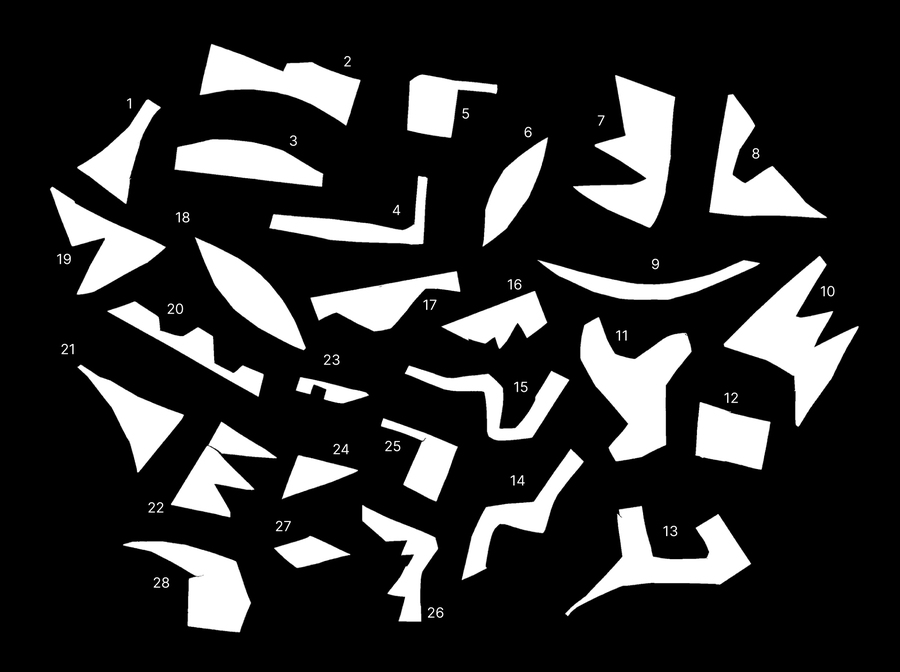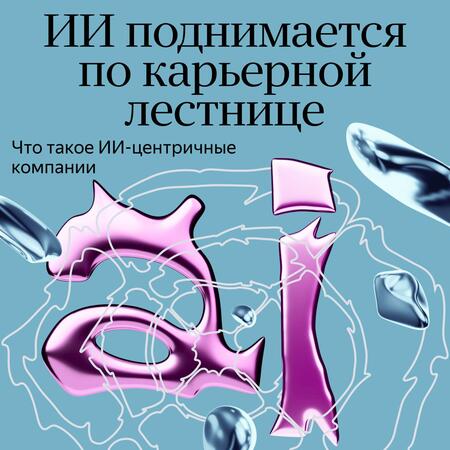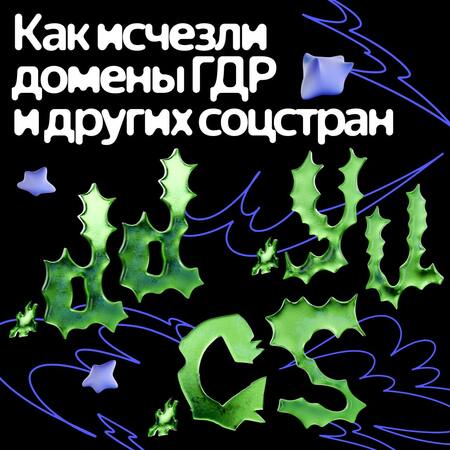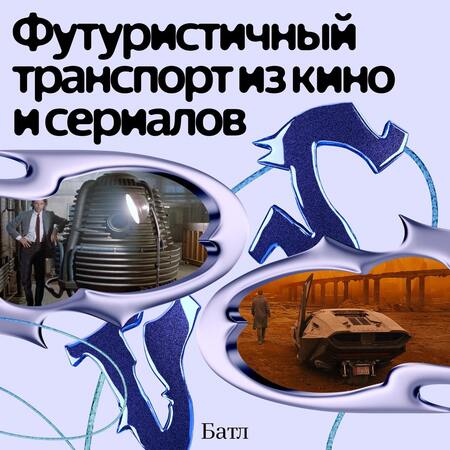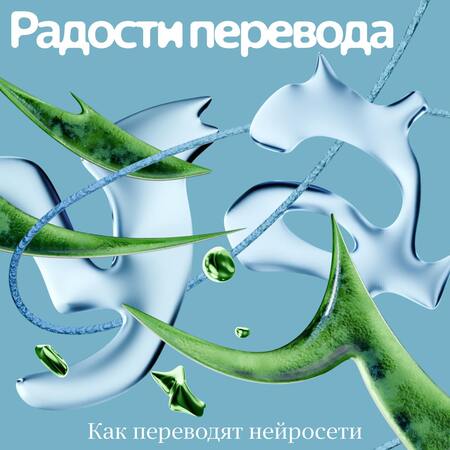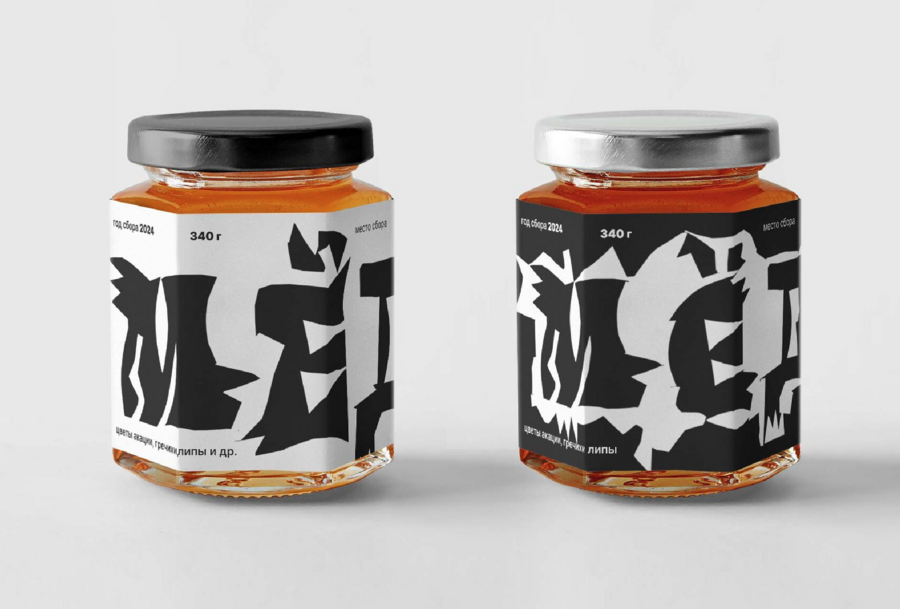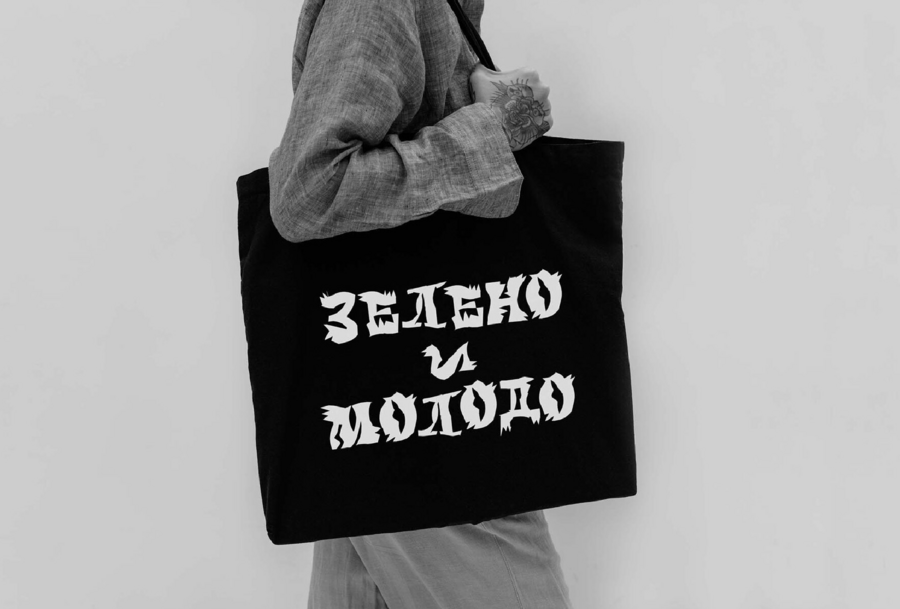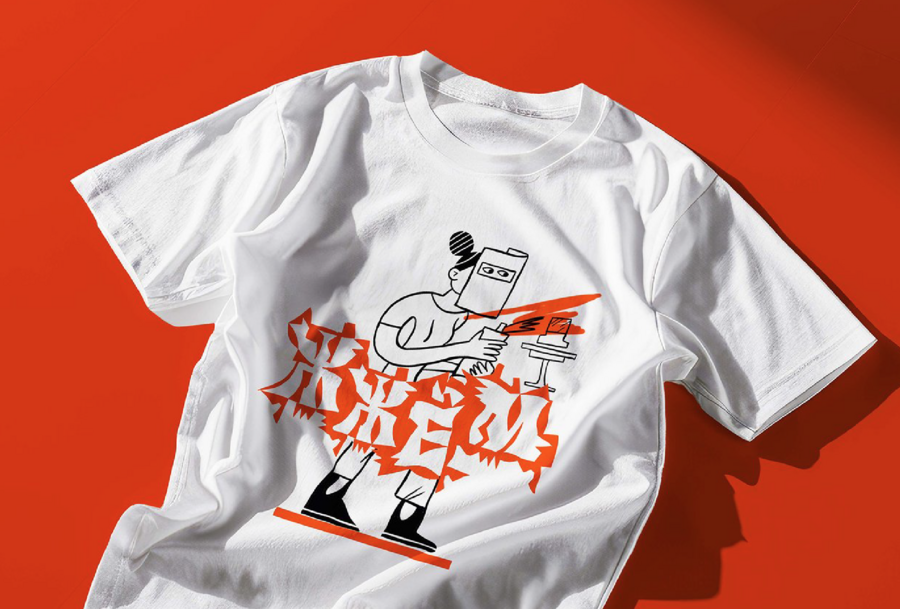
*дръзъ — старославянский смелый, отважный
Этот шрифт про дерзновение. Про решимость начать. Перестать страдать комплексом «вечного студента» («мне еще учиться и учиться» / «Я не готова» и прочее) и начать действовать. Применять полученные навыки на практике и не ждать оценки. Любить своё дело и радоваться тому, что отсутствует равнодушие к своей стезе. Долой серость и уныние! Дръзъ!
Всего у меня было 28 кусочков бумаги, порезанных ножницами.
Мне хотелось найти такой приём, который бы позволял делать буквы быстро, с вариантами форм и при этом был бы мне по духу подходящий. Память обратилась к кусочкам бумаги, которые остались после урока по контрформам. Вот и концепт. Всего у меня было 28 кусочков бумаги. То, что в процессе используется одни и те же решения, только в плюс в создание общей пластики будущей гарнитуры.
Форма, «вытащенная» из контрформы.
Также разработана латиница.
Характер шрифта получился дерзким, угловатым и неоднородным. Из-за некоторых форм букв присутствует даже налет историчности. Легко представить этот шрифт вырезанным в дереве. Гарнитура отлично подходит для акцидентных решений, где необходимо придать характерности сообщению.
Буквы использовались в оформление канала «Техно: Яндекс про технологии» Артдир: Радмила Солнцева граф дизайн: Алена Булгакова 3D motion designer: Сергей Васильев